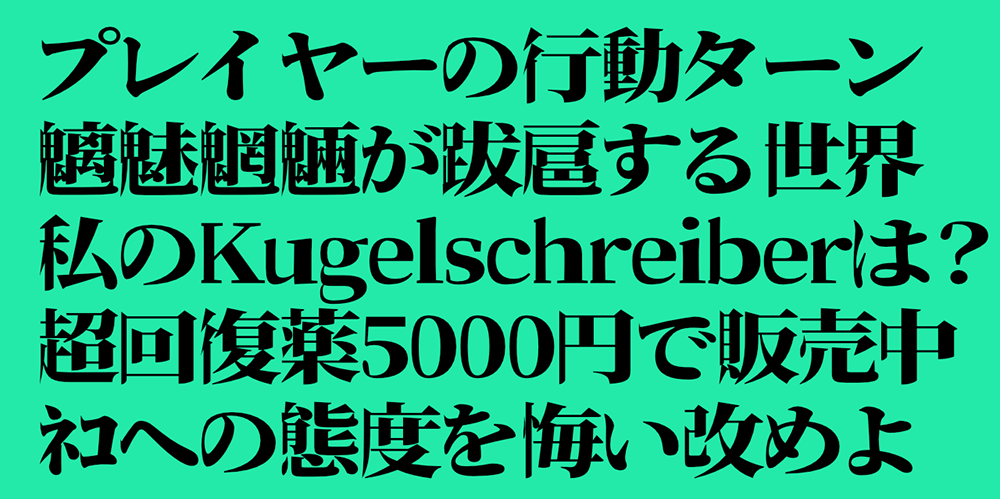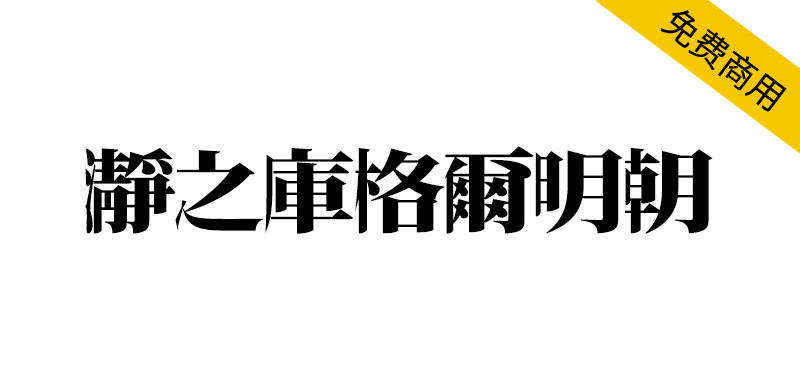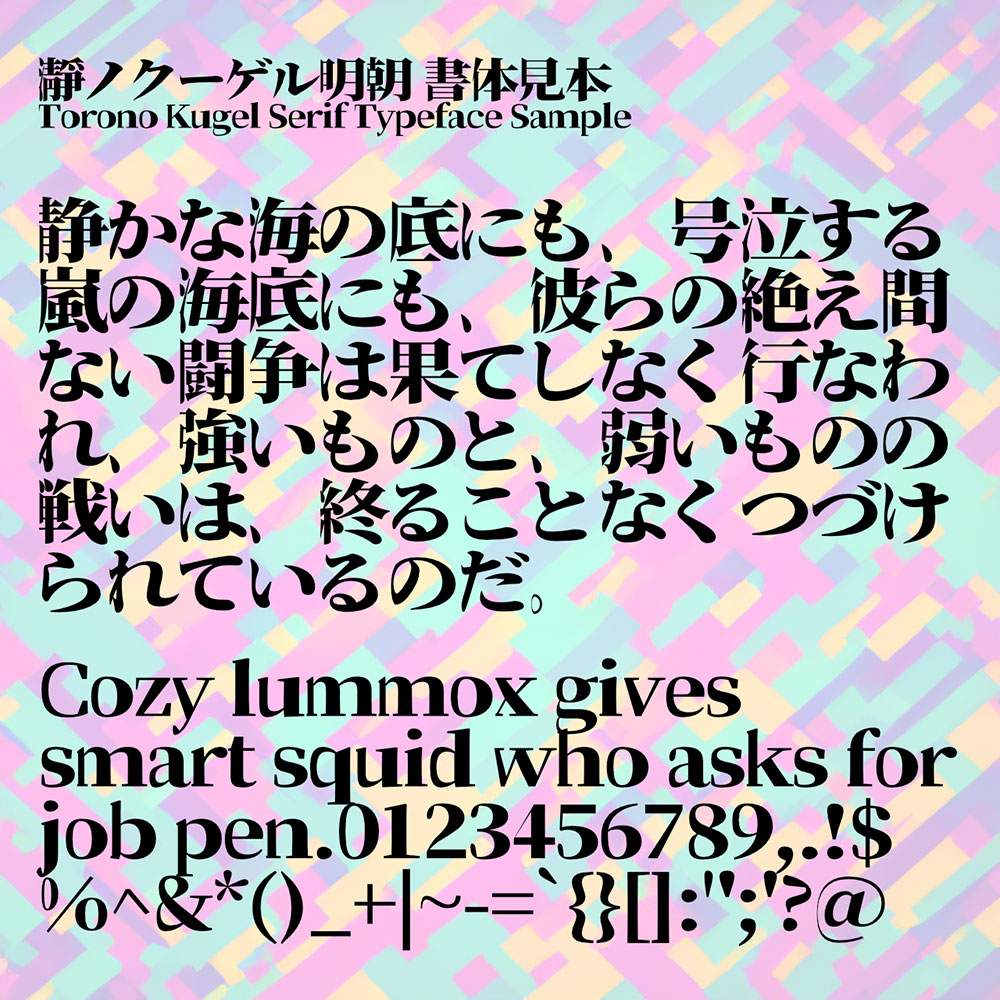
【瀞之库格尔明朝】基于思源宋体对文字右侧进行膨胀化处理
你是否厌倦了千篇一律的字体设计?揭秘瀞之库格尔明朝——这款基于思源宋体的开源字体,大胆对文字右侧进行膨胀化处理,瞬间打造出左扁右宽的动感视觉奇观!灵感源自Fontworks经典Rounded字体,它颠覆传统排版逻辑,让每个字符都充满张力。更关键的是,遵循SIL OPEN FONT LICENSE 1.1协议,完全免费商用、自由修改。设计师们,立即解锁这份独特资源,为你的作品注入不可复制的视觉冲击力!
【瀞之库格尔明朝】基于思源宋体对文字右侧进行膨胀化处理
瀞之库格尔明朝(瀞ノクーゲル明朝)基于思源宋体修改而成,对文字右侧进行了膨胀化处理,形成左扁右宽的视觉效果,其设计灵感源自Fontworks公司的Rounded(ロウディ)字体。瀞之库格尔明朝(瀞ノクーゲル明朝)遵循SIL OPEN FONT LICENSE 1.1开源字体授权协议,允许商用、自由再分发及修改。
【瀞之库格尔明朝】基于思源宋体对文字右侧进行膨胀化处理